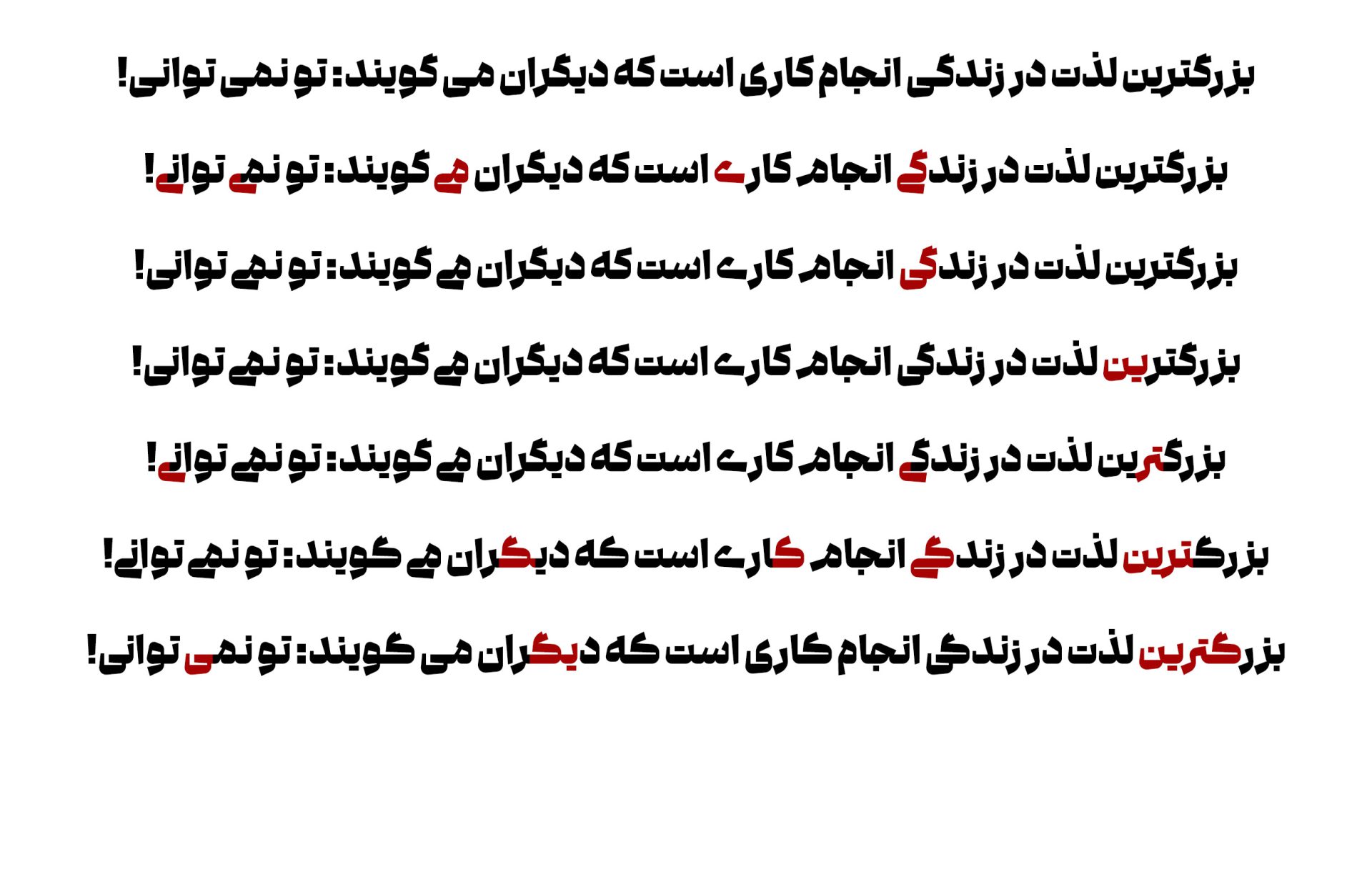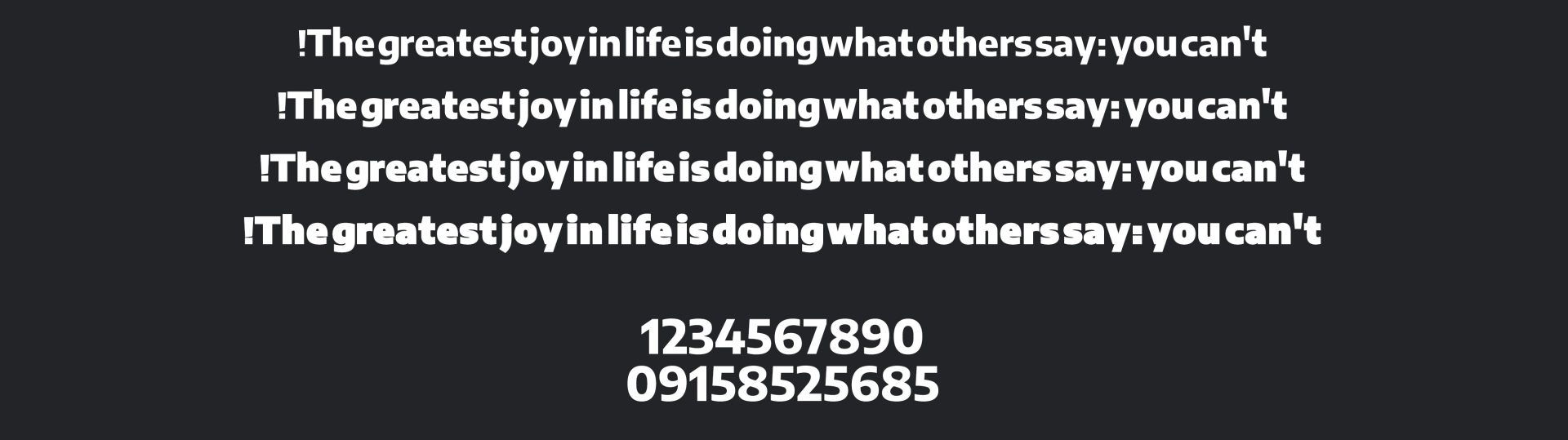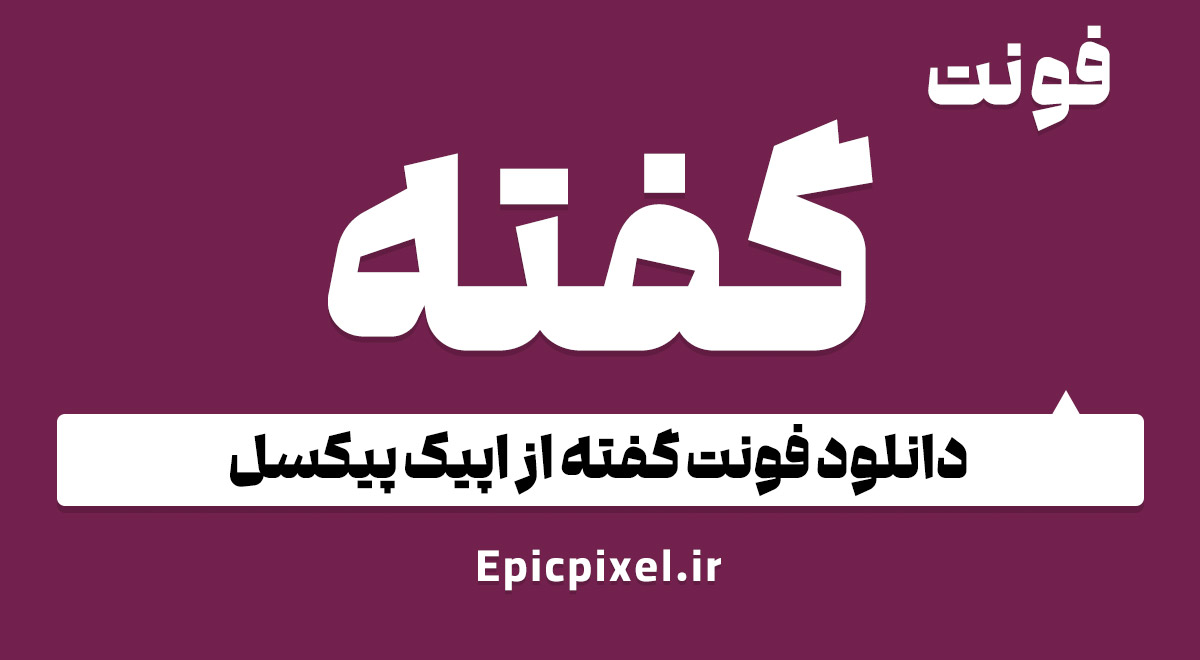
| ⭐ مجموعه فونت | فونت اپیک گفته بولد Epic Gofteh Bold گفته بلک Epic Gofteh black فونت گفته اکسترا بلک Epic Gofteh ExtraBlack اپیک گفته هوی Epic Gofteh Heavy |
| ⭐ توضیحات | نسخه شبیه سازی شده فونت گفته پشتیبانی از حروف فارسی و انگلیسی اعداد فارسی Fu Num و انگلیسی بهمراه نسخه وب |
فونت گفته فریاد جسورانه دنیای تایپوگرافی فارسی
فونت گفته، همانند اسمش، حرفهای زیادی برای گفتن دارد. این فونت از دنیای خط و نوشت بیرون زده و بر بوم طراحی گرافیک، فریاد جسورانه ای از هنر، شخصیت و متمایز بودن را سر داده است. در این دنیای دیجیتالی مملو از فونتهای یکنواخت، گفته با ساختار هندسی منحصربهفرد و روحیه هنری پررنگش، توجه هر بینندهای را به خود جلب میکند.
ویژگیهای خاص فونت گفته چیست
اما ویژگیهای خاص فونت گفته چیست و این فونت در چه کارهایی میدرخشد؟ با من همراه باشید تا سفری به دنیای این فونت دوستداشتنی داشته باشیم:
۱. طراحی هندسی: شکستن قواعد برای خلق زیبایی
فونت گفته را نمیتوان در هیچ قالب از پیشتعیینشدهای جای داد. حروف این فونت، با ضخامتهای متغیر و ساختار هندسی خاص، از قواعد رایج فونتهای فارسی فاصله گرفتهاند. طراح این فونت، علیرضا نعمت الهی، با الهام از خطاطی سنتی و تلفیق آن با طراحی مدرن، دنیای جدیدی از زیبایی را خلق کرده است. شاید در نگاه اول، خواندن حروف گفته کمی چالشبرانگیز باشد، اما همین چالش است که باعث ماندگاری آن در ذهن مخاطب میشود.
۲. روحیه هنری: فریاد جسورانه برای جلب توجه
فونت گفته خاص است. این فونت برای طراحیهای مینیمالیستی و مدرن ساخته نشده است. گفته دوست دارد خودنمایی کند، جلب توجه کند و پیام را با صدای رسا و تاثیرگذار منتقل کند. به همین دلیل، این فونت بهترین انتخاب برای پوسترها، بنرهای تبلیغاتی، کاورهای مجله و هر جایی است که بخواهید حرفتان را بلند و واضح بزنید.
دانلود۳. چند وزن، هزار معنا: انعطافپذیری درون جسارت
اگرچه فونت گفته تنها در 4 وزن طراحی شده است، اما قابلیتهایش فراتر از محدودیتهای وزنی ظاهر میشود. با استفاده از حروف جایگزین (Ligatures) و امکانات OpenType، میتوانید ظاهر گفته را تا حد زیادی شخصیسازی کنید و جلوههای بصری متفاوتی به دست آورید. این ویژگی، دست طراحان را برای خلق آثار منحصربهفرد باز میگذارد.
۴. زبانها در آغوش گفته: فراتر از مرزهای فارسی
دنیای گفته محدود به زبان فارسی نیست. این فونت از حروف لاتین و عربی نیز پشتیبانی میکند و میتواند در کنار همزبانان خود، هارمونی بصری دلنشینی خلق کند. این ویژگی برای طراحانی که با پروژههای چندزبانه سروکار دارند، بسیار باارزش است.
۶. مقایسه با رقبا: شباهتها و تفاوتها
شاید با دیدن گفته، به یاد فونت صنعت بیفتید. هر دو فونت، جسور و دارای ساختار هندسی هستند. اما گفته نسبت به صنعت، ظریفتر و نرمتر است و روحیه هنری بیشتری دارد. همچنین، فونتهای دیگری مانند آبان و پلاک نیز سعی در نوآوری در تایپوگرافی فارسی کردهاند، اما هر کدام سبک و شخصیت خاص خود را دارند.
۷. کاربردهای گفته: در کجا بدرخشد؟
همانطور که اشاره کردیم، گفته برای طراحیهای مدرن و جسورانه مناسب است. در اینجا به چند مورد از کاربردهای اصلی این فونت اشاره میکنیم:
پوسترها و بنرهای تبلیغاتی: گفته توجه مخاطب را جلب میکند و پیام تبلیغاتی را با تاثیرگذاری بیشتری منتقل میکند.
کاورهای مجله و کتاب: استفاده از گفته در کاور، باعث میشود نشریه از سایرین متمایز شود و مخاطب را به خواندن ترغیب کند.
لوگوتایپها و برندینگ: ساختار منحصربهفرد گفته میتواند
زبانها: فارسی، عربی، لاتین
ایدههایی برای خلاقیت بیشتر
استفاده از رنگهای متضاد: برای برجستهتر شدن حروف گفته، از رنگهای متضاد با زمینه استفاده کنید.
ترکیب با فونتهای دیگر: برای ایجاد تنوع، میتوانید گفته را با فونتهای سادهتر ترکیب کنید.
استفاده از حروف جایگزین: با استفاده از Ligatures، میتوانید ظاهری خلاقانهتر به نوشتههای خود ببخشید.
بازی با اندازه حروف: از اندازههای مختلف حروف گفته برای ایجاد سلسله مراتب بصری در متن خود استفاده کنید.
جمعبندی
فونت گفته یک فونت خاص و جسورانه است که برای طراحیهای مینیمالیستی و مدرن مناسب نیست. این فونت برای جلب توجه، فریاد زدن پیام و ایجاد تمایز در دنیای تایپوگرافی فارسی طراحی شده است. اگر به دنبال فونتی هستید که منحصربهفرد، هنری و تاثیرگذار باشد، فونت گفته را امتحان کنید.
۱. آیا فونت گفته برای خواندن متنهای طولانی مناسب است؟
به دلیل ساختار هندسی خاص و ضخامت متغیر حروف، فونت گفته برای خواندن متنهای طولانی مناسب نیست. بهتر است از این فونت برای عناوین، تیترها و متنهای کوتاه استفاده شود.
۲. چگونه میتوانم از حروف جایگزین (Ligatures) در فونت گفته استفاده کنم؟
برای استفاده از Ligatures، باید از نرمافزاری استفاده کنید که از OpenType پشتیبانی میکند. در این نرمافزارها، میتوانید با فعال کردن گزینه Ligatures، از حروف جایگزین گفته استفاده کنید.
۳. آیا فونت گفته برای استفاده در وبسایت مناسب است؟
۴. چه فونتهایی با فونت گفته همخوانی دارند؟
فونتهایی مانند فونت یکان،فونت وزیر و فونت صمیم میتوانند با فونت گفته همخوانی داشته باشند.
دانلود۵. آیا فونت گفته برای طراحی لوگو مناسب است؟
بله، فونت گفته میتواند برای طراحی لوگوهای خاص و خلاقانه استفاده شود.